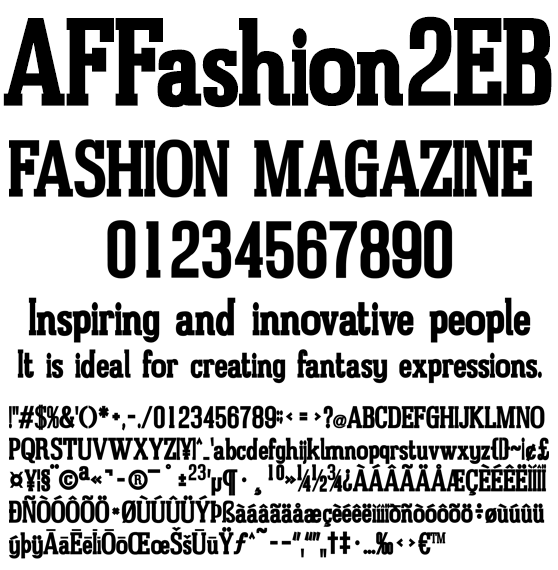
ファッション系 欧文ォント AFFashion2EB
AFFashion2EB
狭いサイドベアリングに強カーニングでファッション系に最適なエクストラボールドウェイト欧文フォントです。ドキュメント、写真、動画テロップ、WebPage などにいかがでしょうか。パンフレット、リーフレット、フライヤー、ファッション系コンテンツに使えるフォントです。日本のローマ字表記で使われる訓令式やヘボン式で扱う Ô や Ō を収録、人名地名へのアプローチもリアルです。